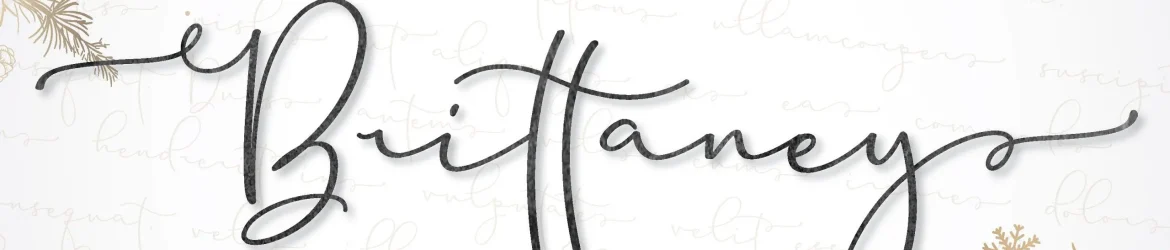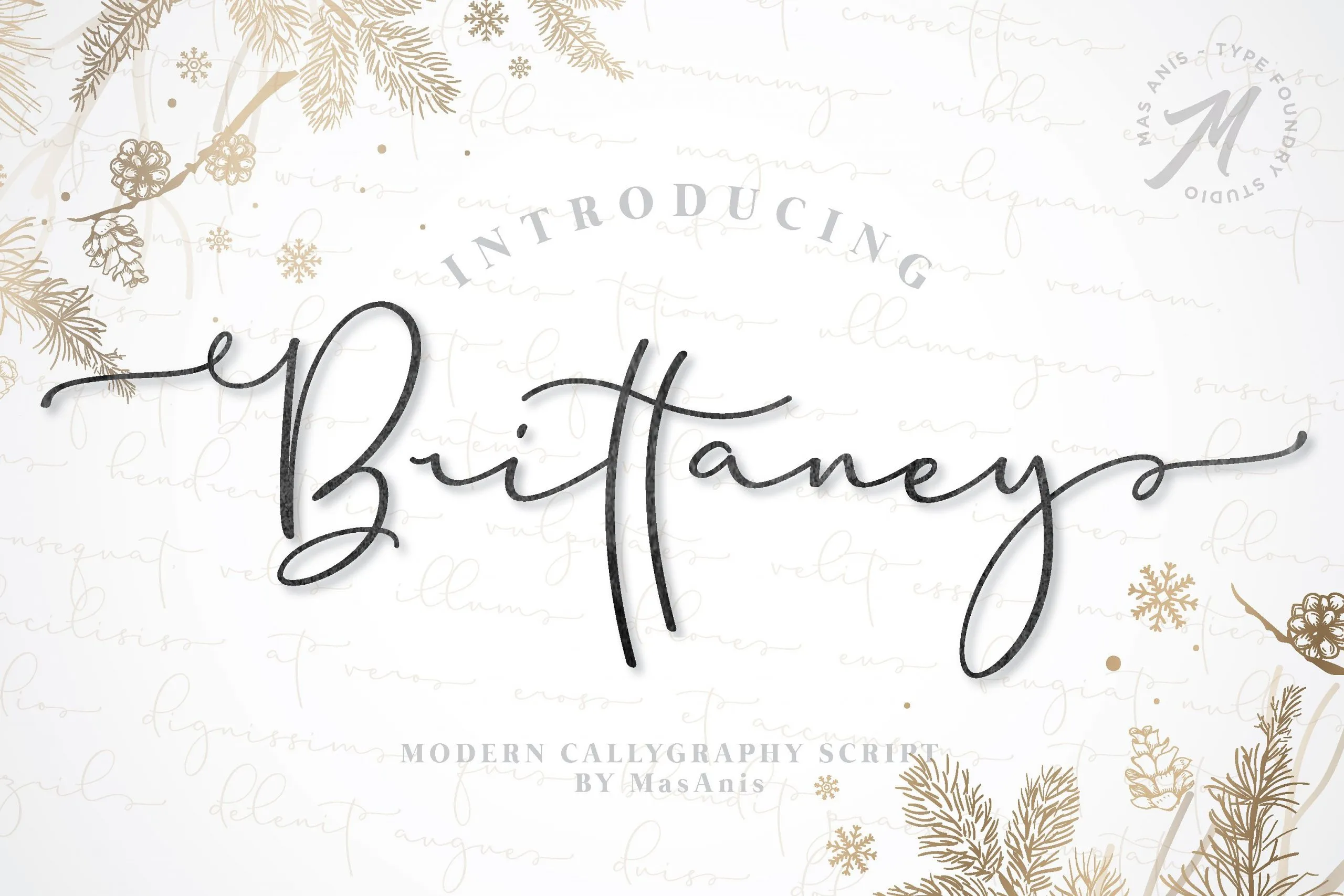
Brittaney Script Font
A nova fonte britannica moderna é perfeita para projetos que buscam sofisticação e elegância. Inspirada no estilo da escritura moderna com alternativas estilizadas para textos, a Brittaney Script Font oferece um toque natural e refinado de ligaturas, tornando-a versátil em uma ampla variedade de aplicações. Perfumados de seu charme, este fonte é perfeito para criar selos de empresa, menus elegantes ou até mesmo cartas de casamento. Seja para adicionar um toque distintivo a sua identidade empresarial, dar um ar sofisticado às suas festas nupciais ou transformar uma simples refeição em um ato culinário de alto nível, Brittaney Script Font tem tudo o que você precisa. Talvez você ainda não tenha aproveitado todo o potencial deste fonte para projetos de mídia social. O estilo elegante e moderno de Brittaney Script cria um texto vibrante e único, certamente tornando seus posts mais atraentes e memoráveis. E em uma era onde cada detalhe conta, esta fonte é definitivamente recomendada para aquelas oportunidades especiais que merecem muito mais. Seja você um designer gráfico ou simplesmente alguém que ama criar algo especial na web, Brittaney Script Font oferece uma maneira perfeita de destacar seus trabalhos e torná-los ainda mais memoráveis.